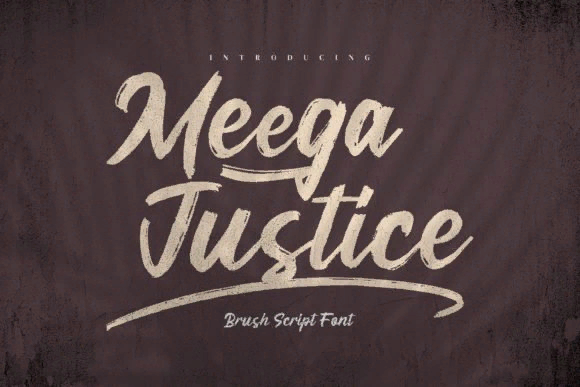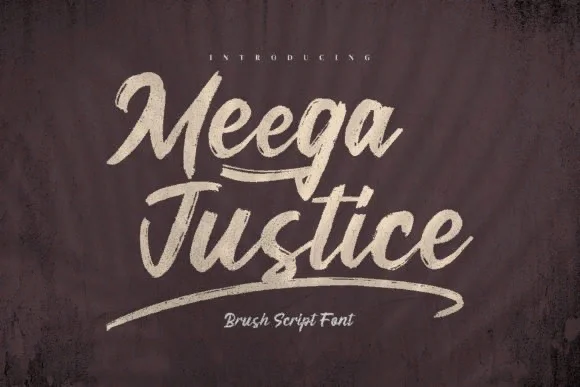
Название: Meega Juctice Font (2021)
Meega Juctice - очаровательный рукописный шрифт.
Этот универсальный шрифт имеет широкий спектр применения - от поздравительных открыток до заголовков - и гарантированно придаст романтический настрой вашему следующему проекту.